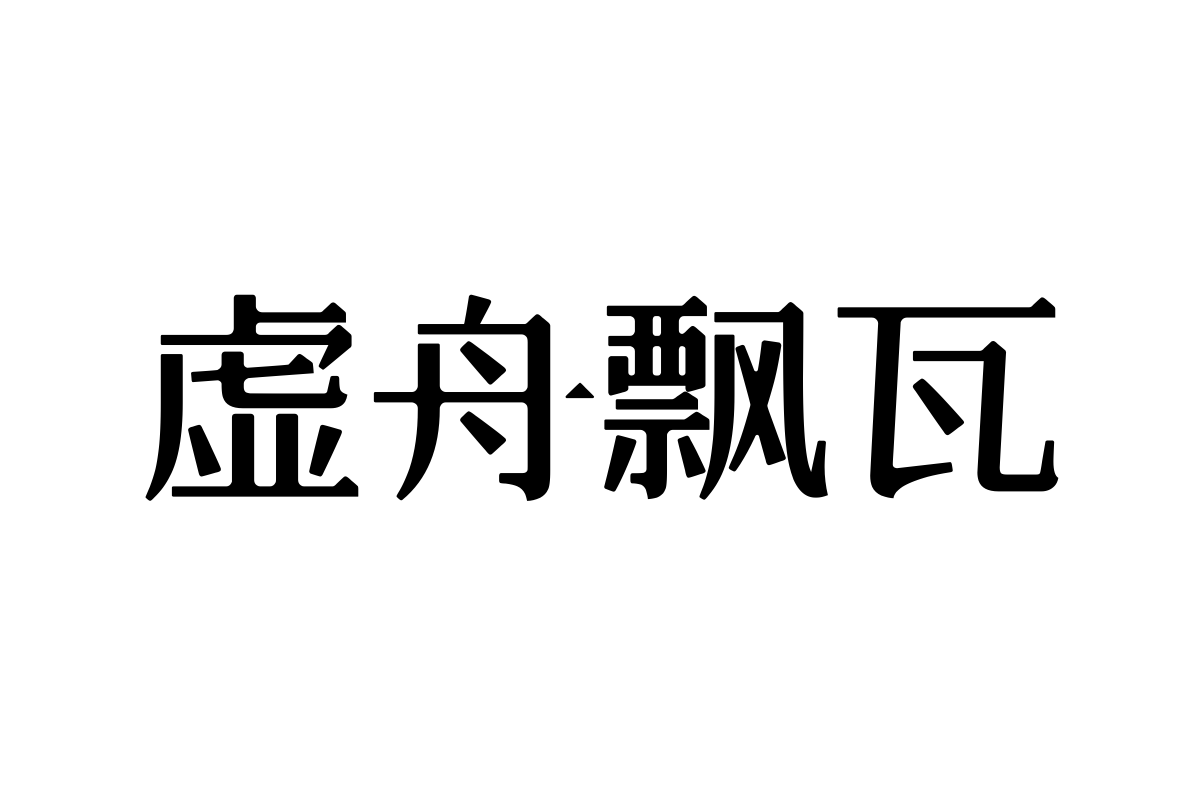
上首中正宋体是一款具有独特风格的中文字体,它结合了传统书法的韵味与现代设计的理念。这种字体的特点是笔画流畅、结构均衡,给人一种优雅而庄重的感觉。
上首中正宋体的字形特点是笔画粗细适中,既有楷书的规整感,又有行书的流畅性。它的结构严谨,每个字都经过精心设计,以确保整体的和谐与美感。
此外,上首中正宋体还注重细节的处理,如字间距、行间距等,使得整个字体看起来更加美观大方。同时,该字体还具有一定的可读性,适合用于各种正式场合的文字展示。
总之,上首中正宋体是一款非常优秀的中文字体,无论是在设计还是在日常书写中都能展现出其独特的魅力。